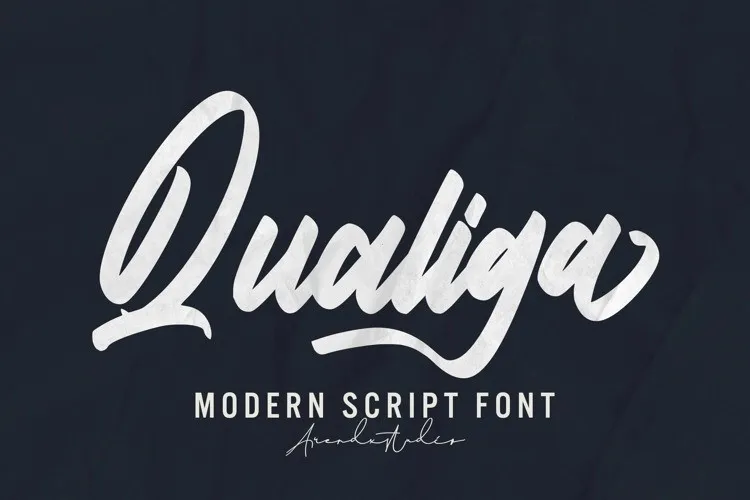
Qualiga Font – Download Grátis
A Qualiga Font é uma elegante fónta script criada para designers que buscam transmitir simplicidade e modernidade em seus projetos visuais. Com traços finos e letras geométricas, ela combina a delicadeza do estilo cursive com um toque de sofisticação, resultando em fontes modernas e elegantes. Ideal para criações como logotipos, bandaianas, capas de livros ou embalagens, ou até mesmo camisetas personalizadas, a Qualiga oferece recursos avançados, incluindo alternativas estilizadas, conjuntos de caracteres estilizados e ligaturas, para garantir um resultado profissional em todas as aplicações. Seja qual for o seu projeto, a Qualiga é uma escolha versátil que adicionará personalidade à sua criação com os mínimos detalhes necessários.